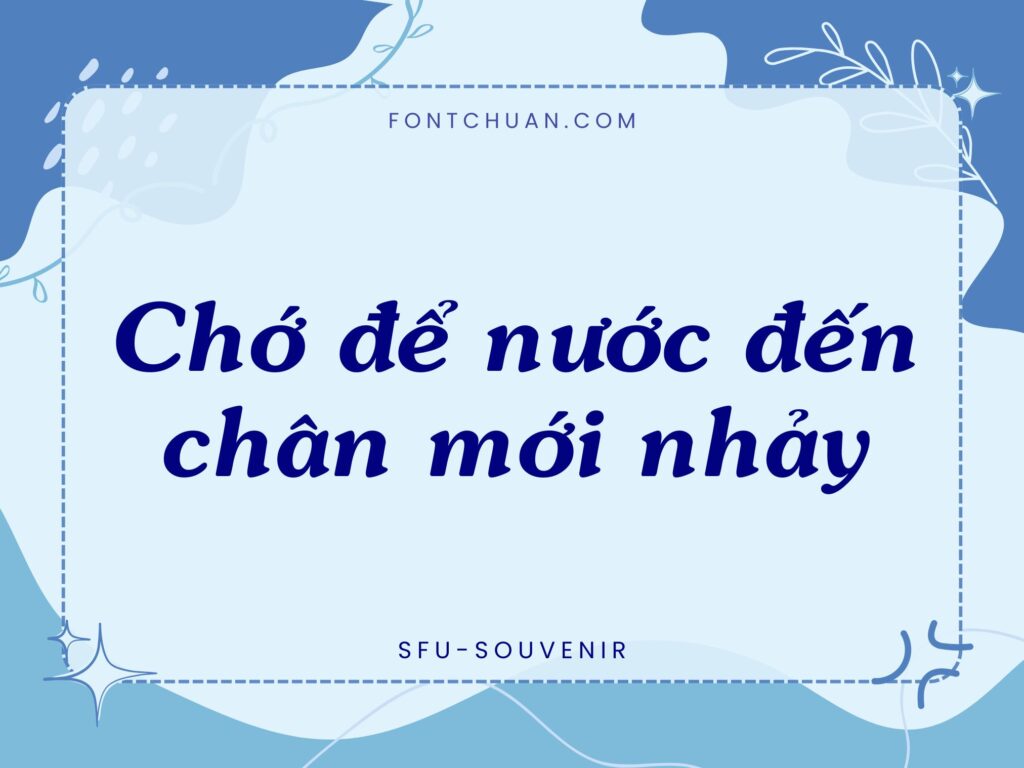
Font SFU Souvenir Việt Hóa
Font SFU Souvenir Bold là một kiểu chữ serif cổ điển, được thiết kế với các đường nét mềm mại và uyển chuyển, tạo cảm giác thân thiện và dễ đọc. Font này thích hợp cho nhiều mục đích sử dụng khác nhau, từ văn bản nội dung đến tiêu đề và thiết kế đồ họa.
SFU Souvenir Bold lý tưởng cho các dự án thiết kế logo, tiêu đề, bao bì sản phẩm và các ấn phẩm quảng cáo. Các ngành nghề như quảng cáo, giáo dục và công nghệ có thể tận dụng font này để tạo điểm nhấn trong thiết kế. Ngoài ra, font cũng thích hợp cho các sự kiện như Tết, Giáng sinh, Valentine và các lễ hội khác.